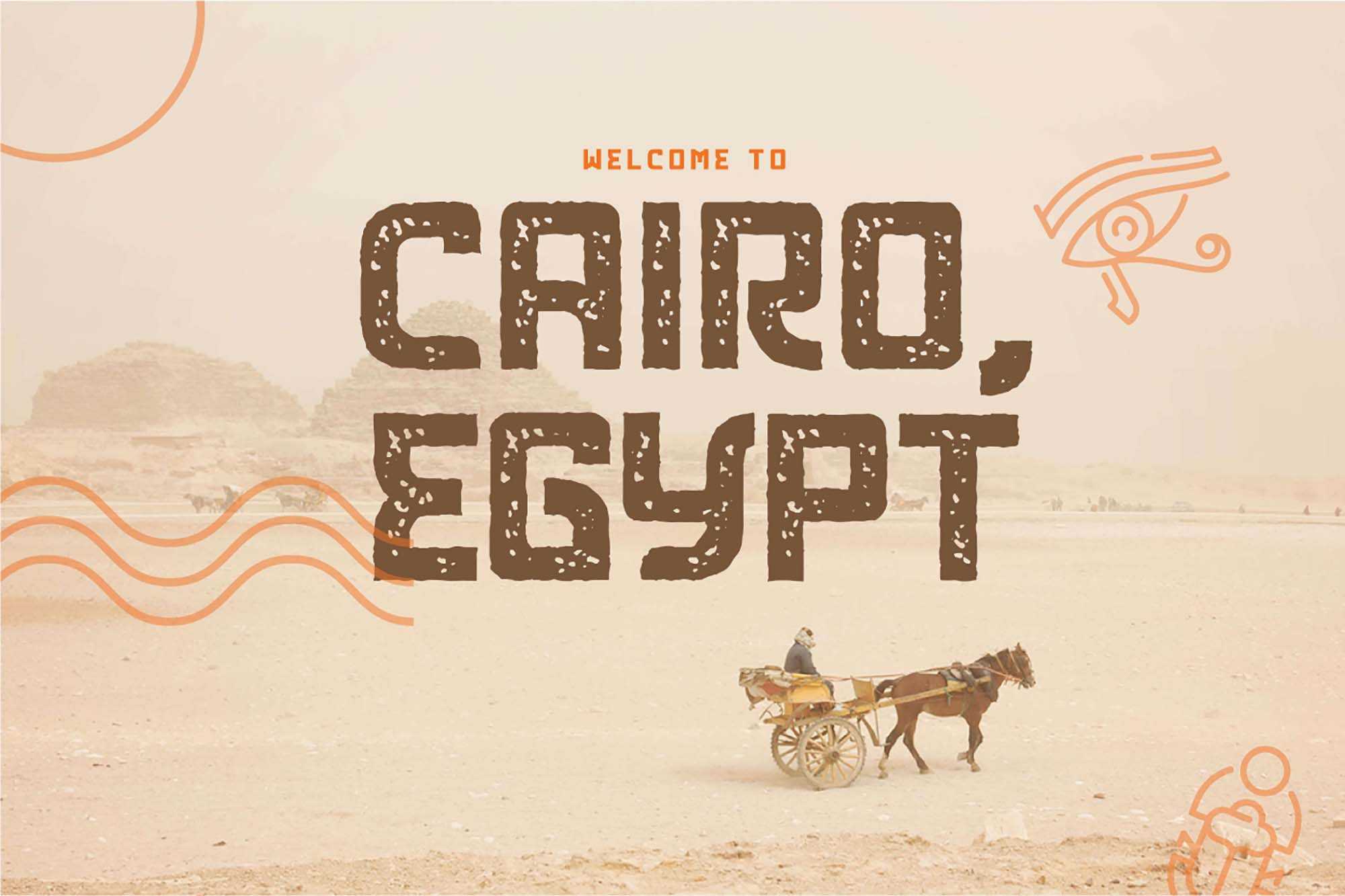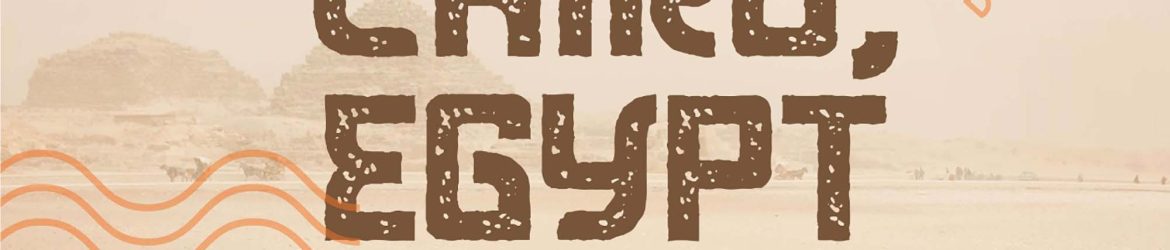
Khepri Egyptian Typeface – Download Grátis
A fonte de tipo Khepre é uma paixão para os amantes de arte antigas. Inspirada nas magníficas hieróglifos egípcios, essa fonte permite que você crie textos que transmitem a magia da antiguidade. As belas formas e cores da hieróglifo proporcionam um contraste encantador entre o texto e o fundo, criando uma harmonia perfeita. Perfeita para designers que querem dar um toque único e histórico a seus projetos, Khepre é o recurso gráfico perfeito para quem quer transportar seus trabalhos para o mundo do antigo Egito. Uma fonte que não apenas escreve, mas faz você viajar no tempo.